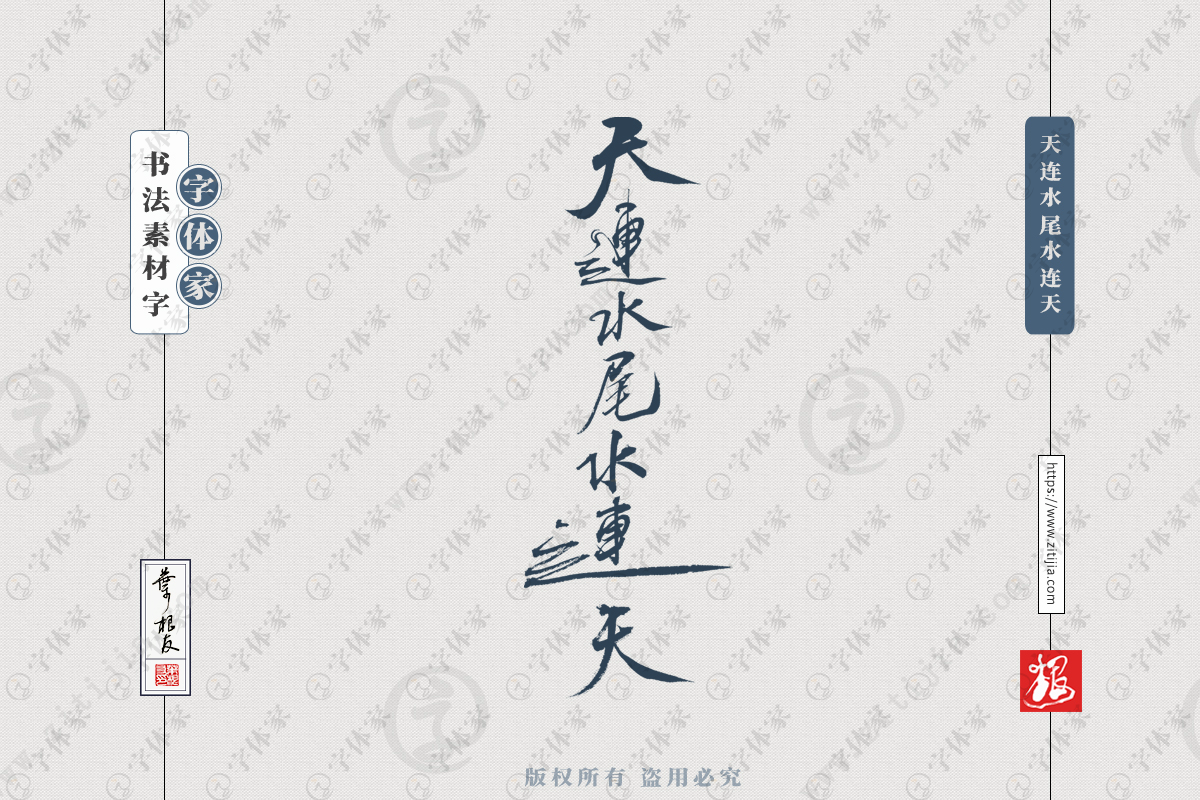
字体家提供叶根友手写天连水尾水连天书法字体设计可下载源文件书法素材
““天连水尾水连天”的上一句是雾锁山头山锁雾。这是一副回文对联,就是上下联从最后一个字往前倒着念也可以成一副对联。意思就是说大雾弥漫,看不清远处的山峰;水天一色,天水相接。顶针联,亦称联珠对、联锦对,是指对联的前一个分句的句脚字,作为后一个分句的句头字,使相邻的两个分句,首尾相连,一气呵成。如“山羊上山,山碰山羊角;水牛下水,水没水牛腰。”顶针联,按顶针单位分为字顶针、词顶针等,按联中的顶针位置,可分为句中顶针、句间顶针和句句顶针。”